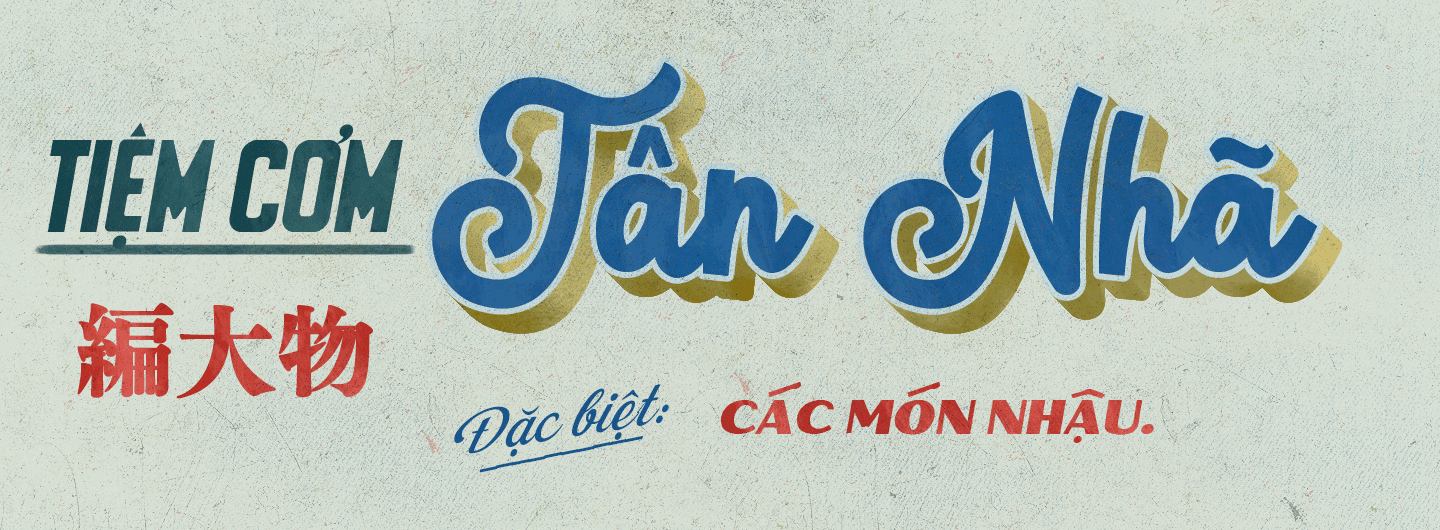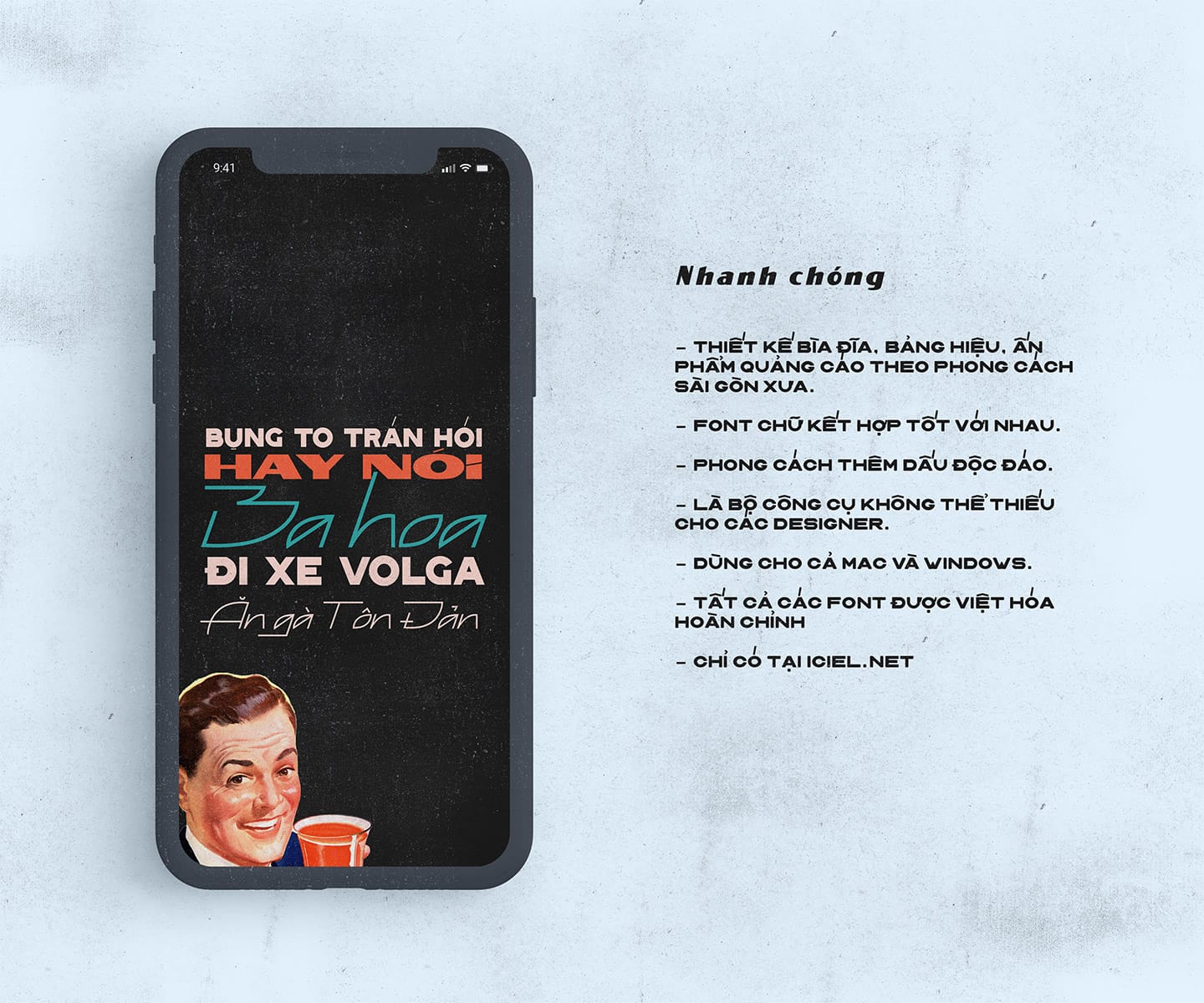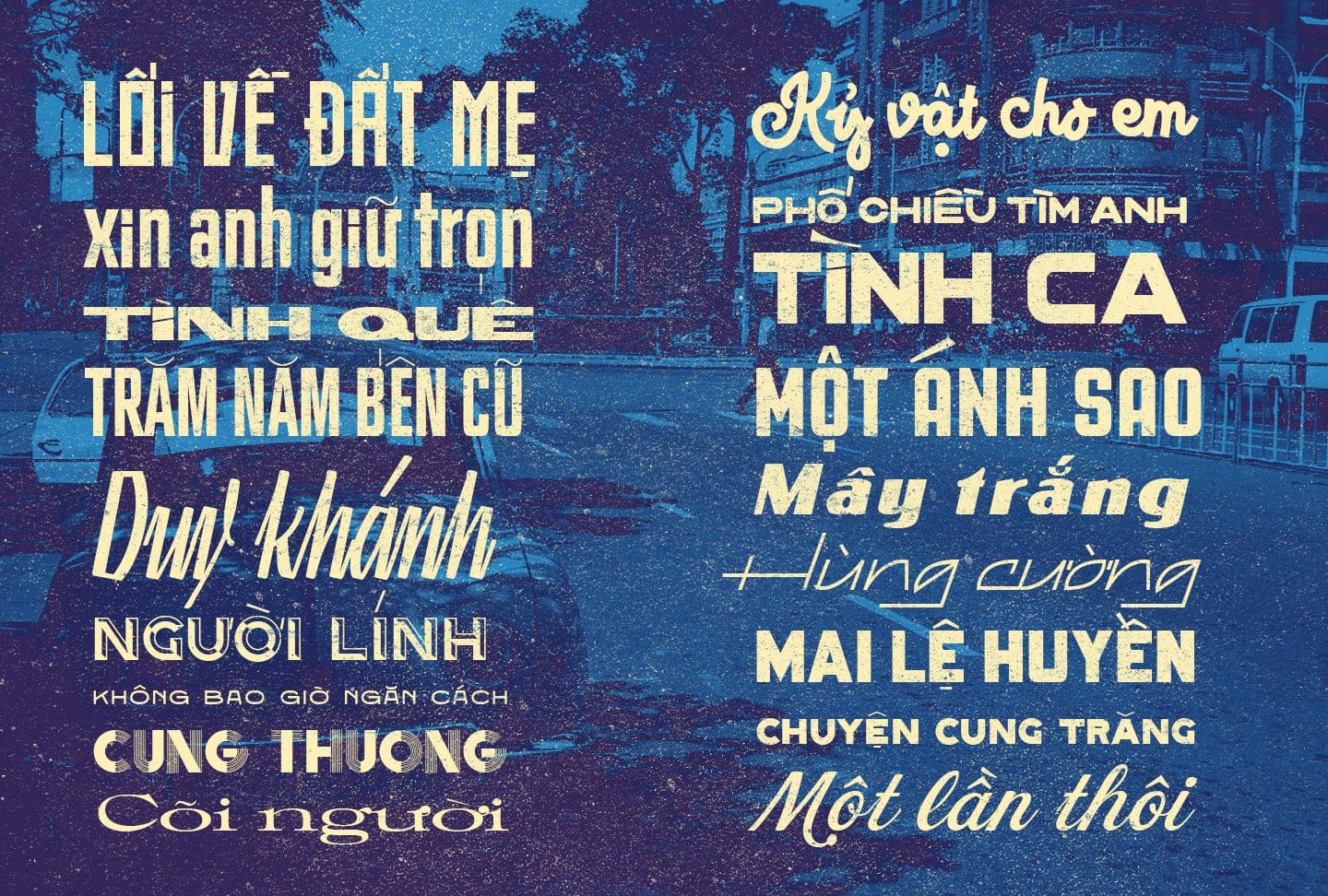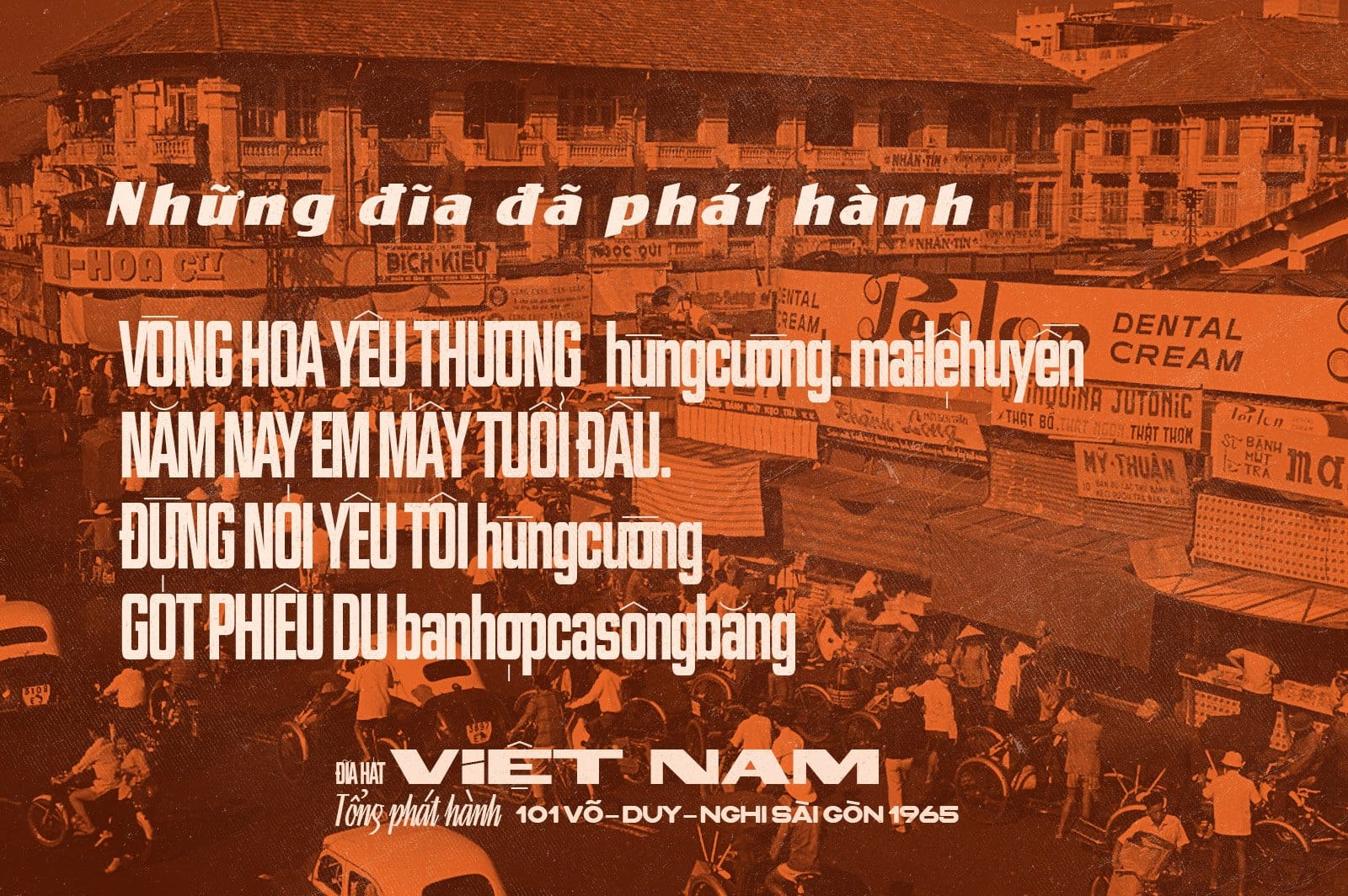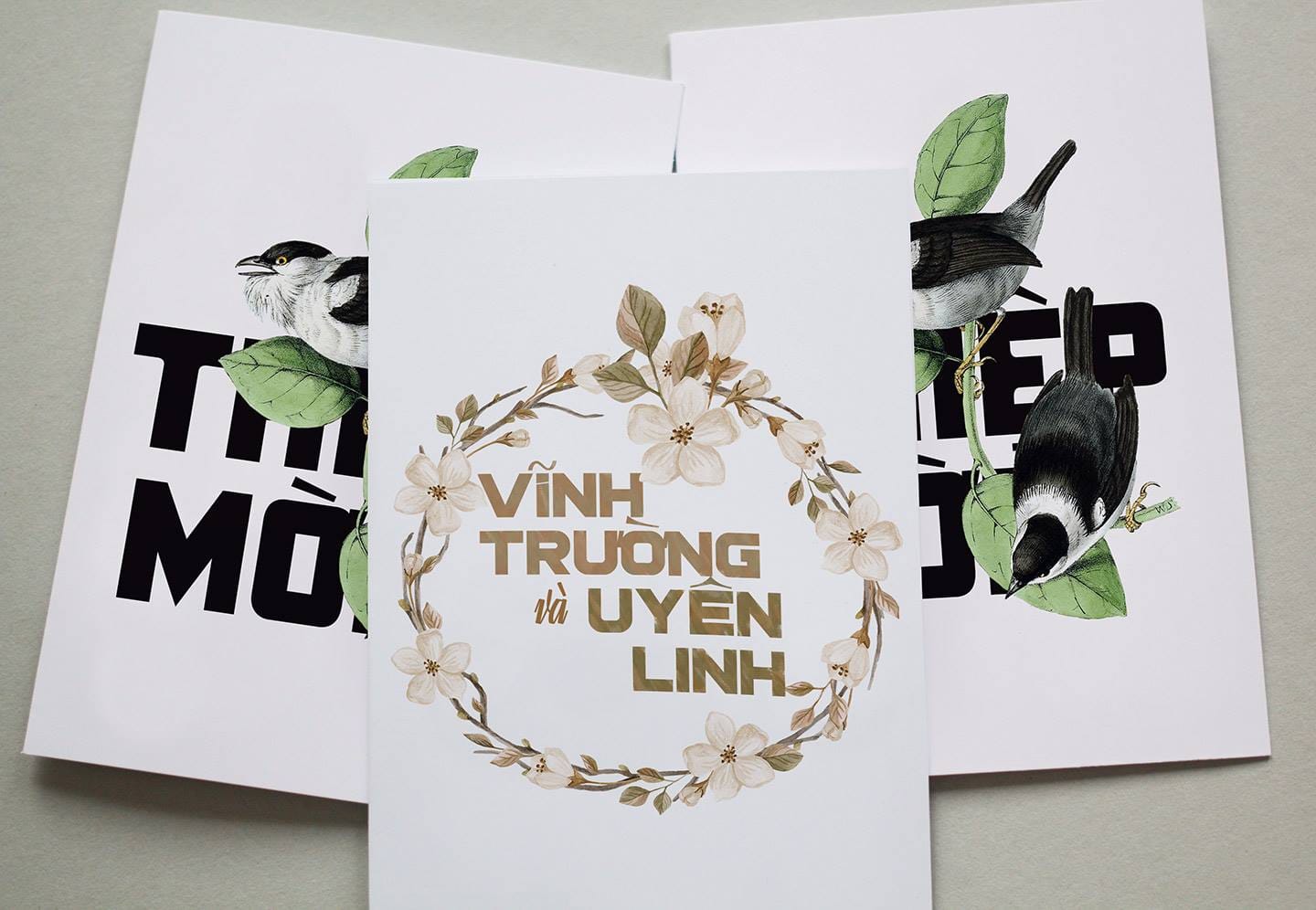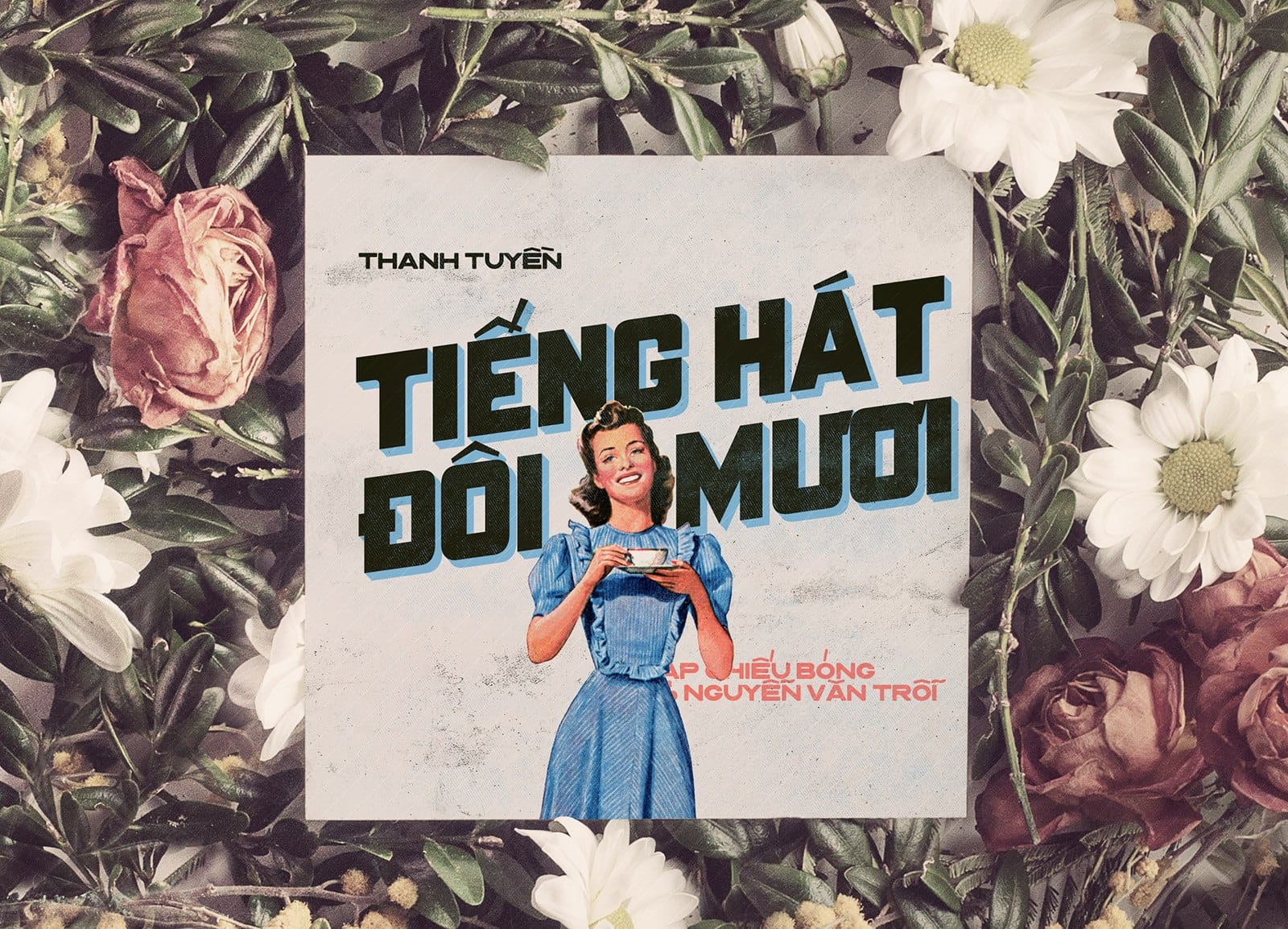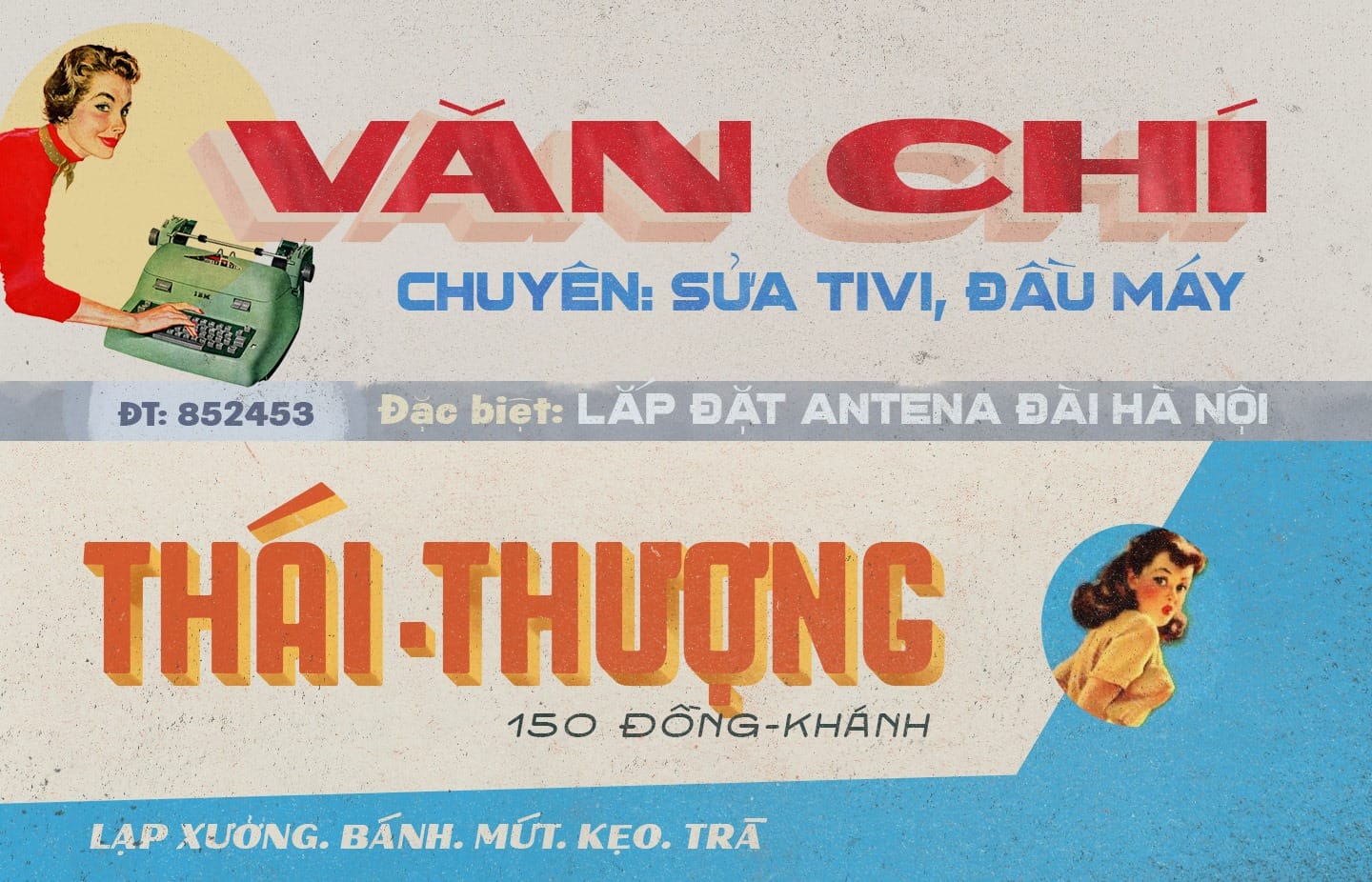
Tiếp tục với font xưa cũ Việt Hóa, đây là bộ font Nam Kỳ Diễn Ca bao gồm 29 font Việt Hóa bởi iCiel được lấy cảm hứng từ bảng hiệu thời xưa. Đây là bộ font vintage cực kỳ ấn tượng với cảm hứng lấy từ các typography trên các bìa đĩa CD nhạc thời xưa. Đây là bộ font mình đã mua full với giá 650k và sẽ chia sẻ giới hạn cho thành viên DafontVN. Nếu có điều kiện hãy ủng hộ tác giả nhé.
trước đó đã được sử dụng rất nhiều trên các ấn phẩm văn hóa đại chúng như các tạp chí, bìa sách của nhà sách Nhã Nam, các thiết kế của Cộng Cà Phê… trong đó mình cũng đã sử dụng bộ font này cho các thiết kế ở công ty, bộ font xưa cũ Việt Hóa này của iCiel thực sự là rất chất lượng.
Bộ font Nam Kỳ Diễn Ca – Full 29 font Việt Hóa bao gồm:
– 29 font chữ việt hóa theo phong cách xưa cũ, bao cấp/Sài Gòn xưa.